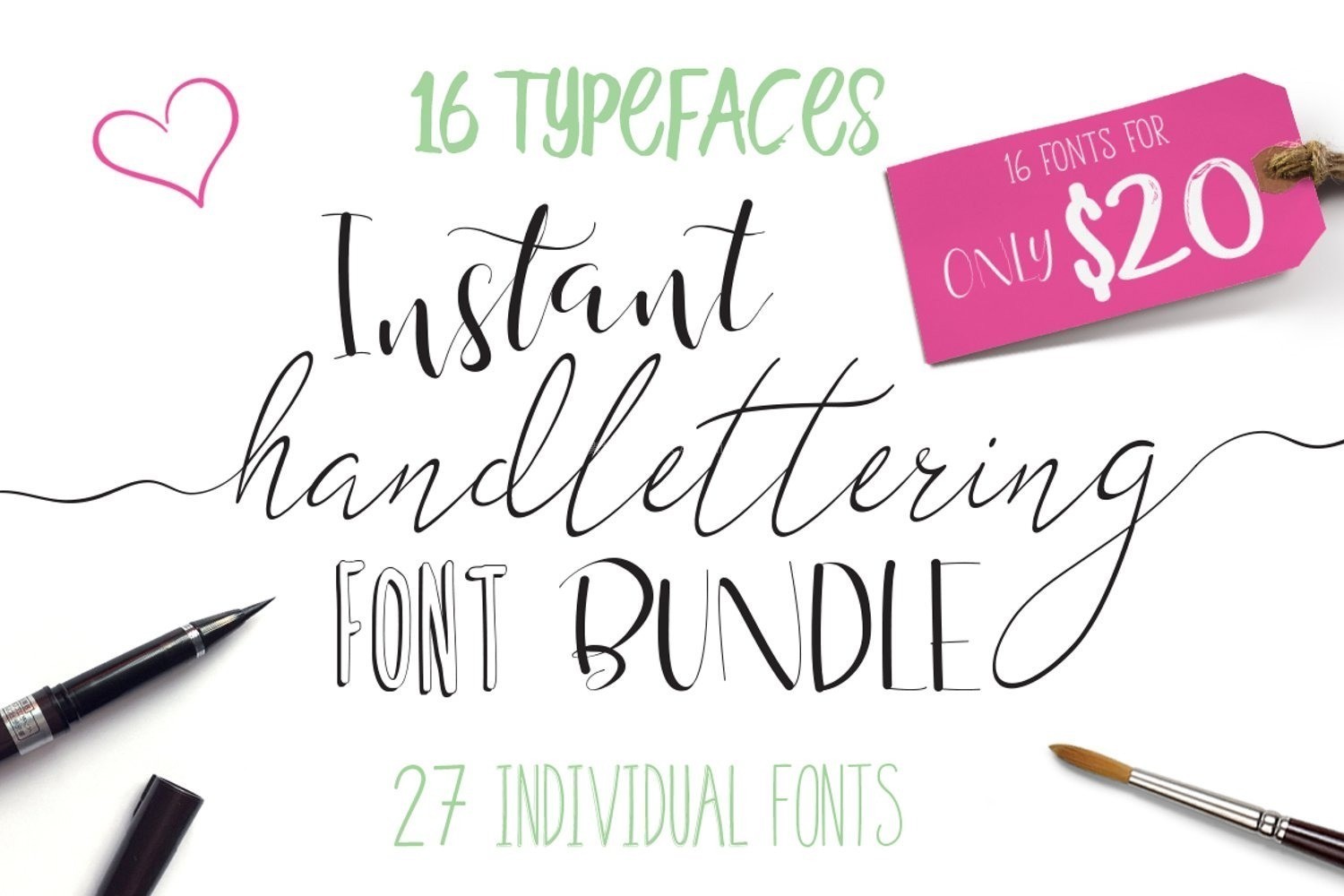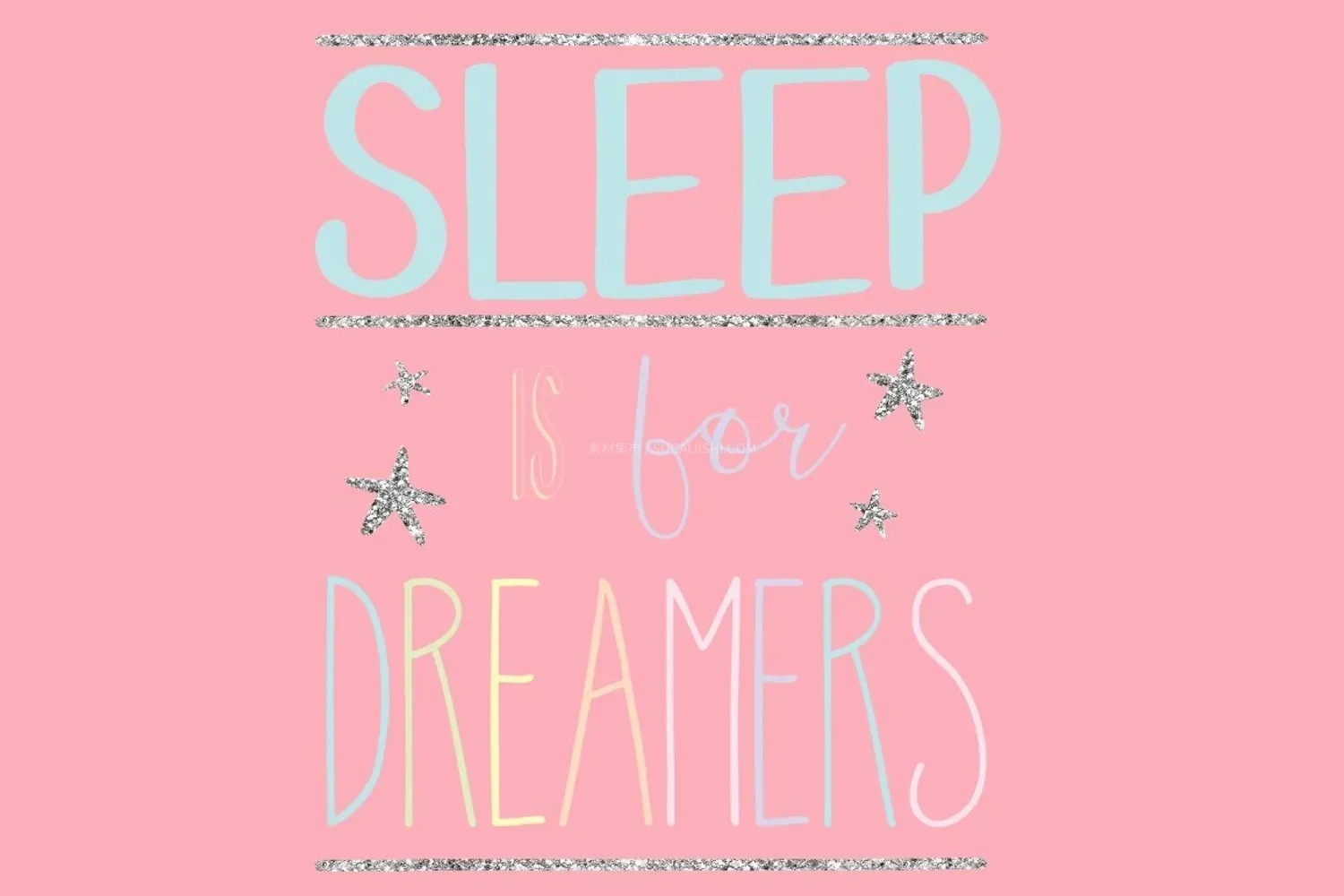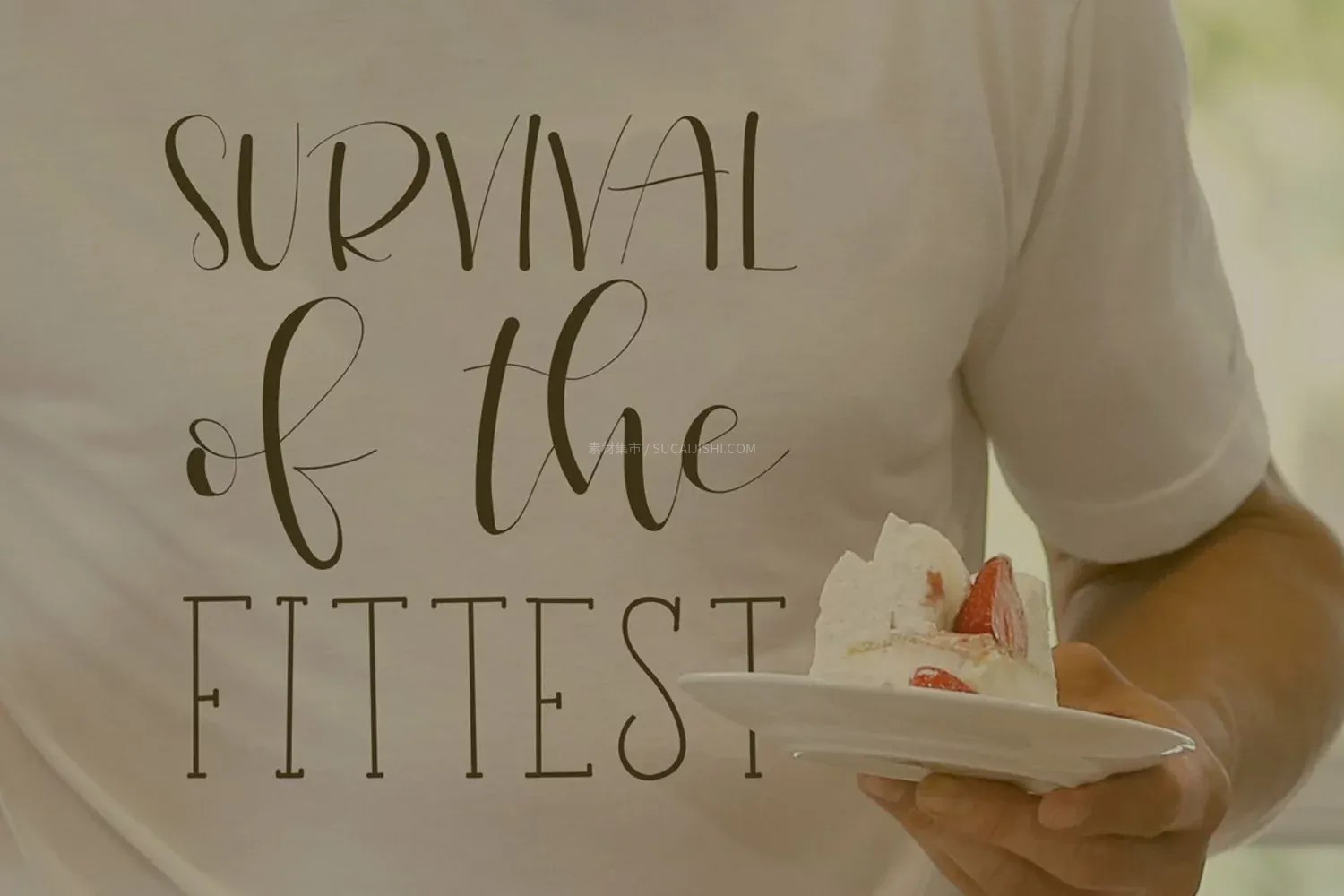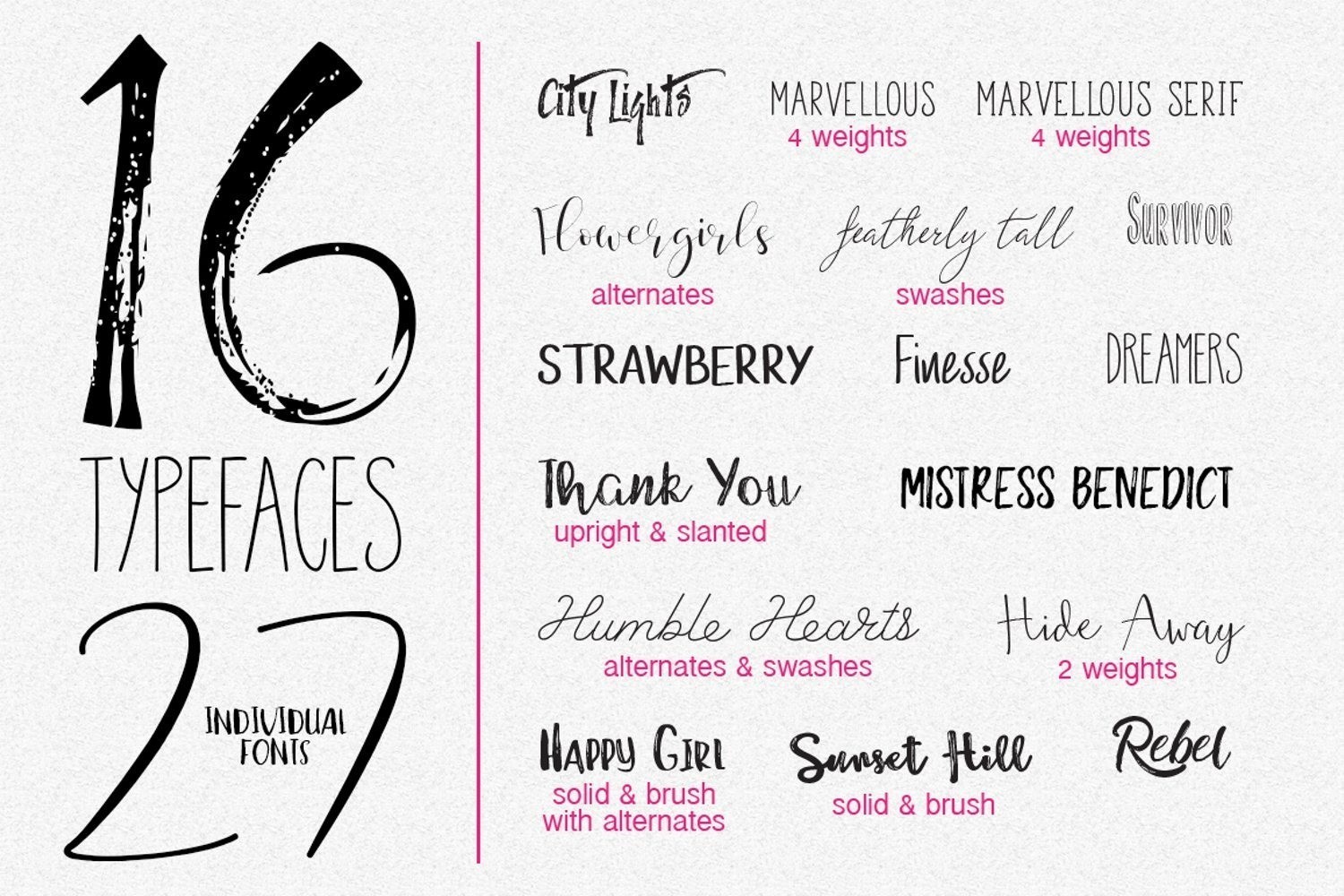
16款高质感手写字体合集
这是一套专为设计师打造的超值字体套装。合集核心包含16款精选字体,其中10款为全新发布的款式。实际包含27款独立字体文件,涵盖了从优雅书法到动感马克笔刷等多种手绘风格。多数字体支持替代字形(Alt Glyphs)与连字功能(Ligatures),并完美适配国际字符,适用品牌形象设计、海报标题、包装设计、婚礼请柬、社交媒体配图、手账拼贴、Logo设计、个人艺术创作等。
包含字体列表:
City Lights - NEW! 城市霓虹感
Marvellous (包含4种粗细) - NEW! * Marvellous Serif (包含4种粗细) - NEW!
Flowergirls - NEW! 甜美清新
Featherly Tall - NEW! 纤细高雅
Survivor - NEW! 粗犷有力
Strawberry - NEW! 俏皮可爱
Finesse - NEW! 精致笔触
Dreamers - NEW! 梦幻手写
Thank You (包含2款字体) - NEW!
Mistress Benedict / Humble Hearts / Hide Away (2种粗细)
Happy Girl / Sunset Hill / Rebel